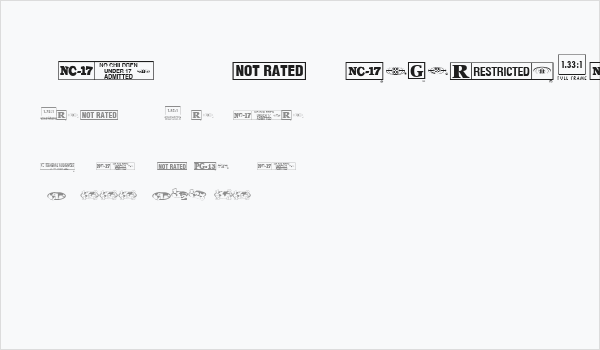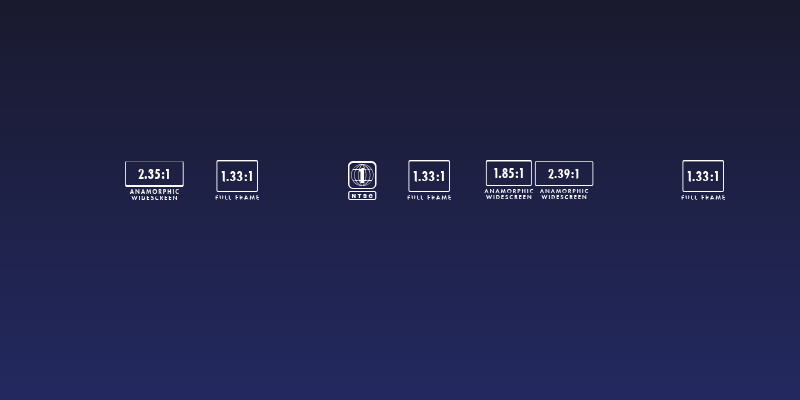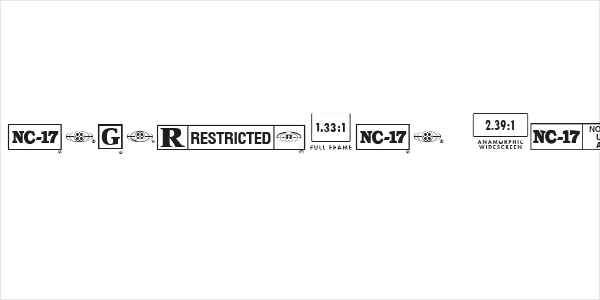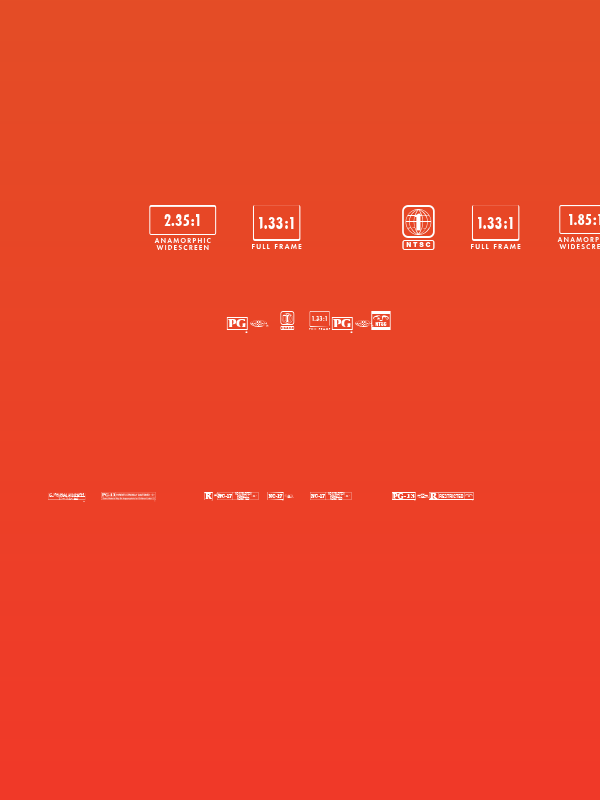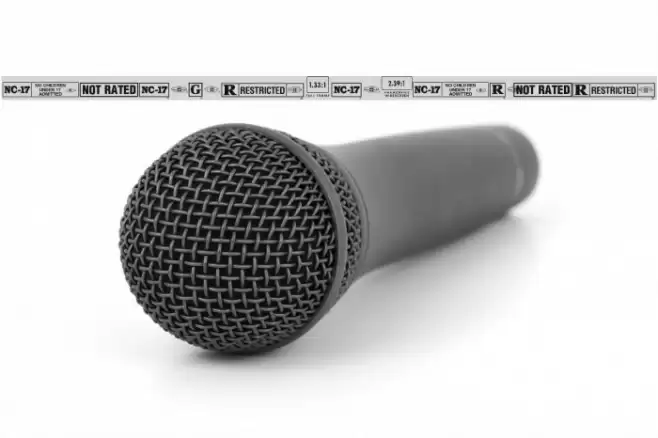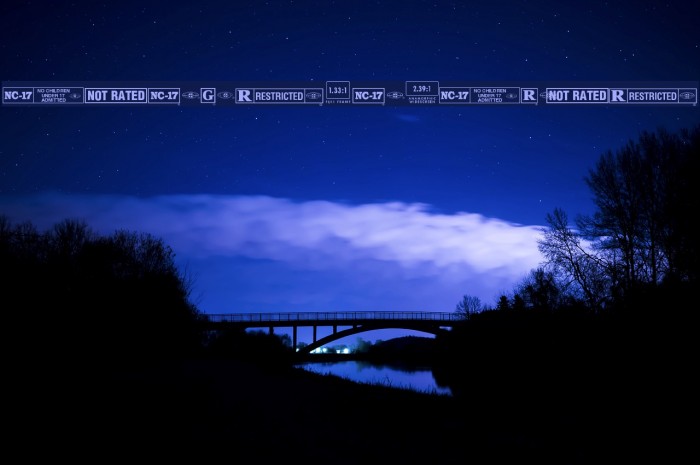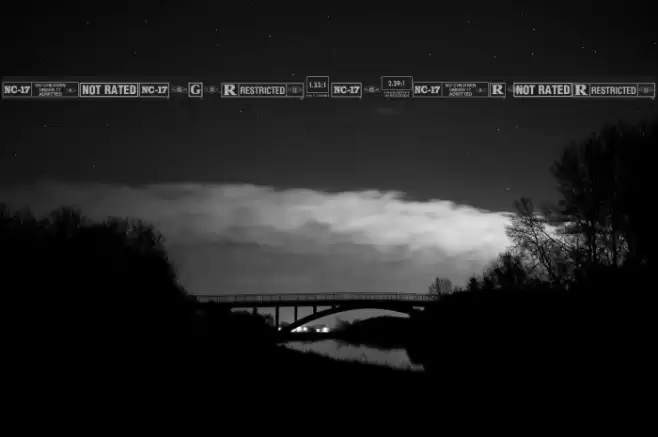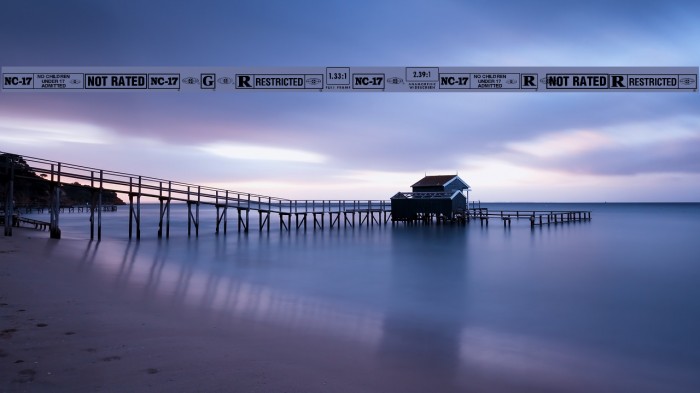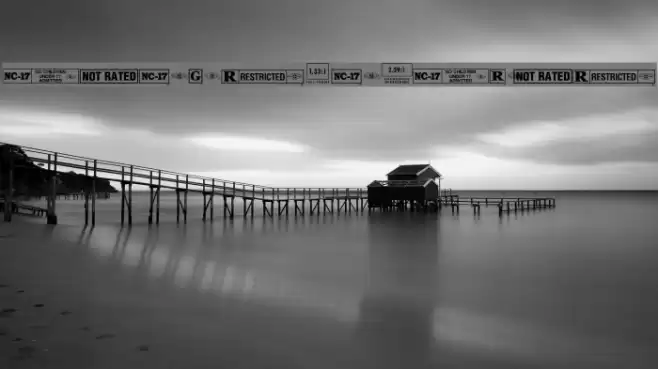
MovieRatingsAndFormats Font
| Style général | Utilitarian, Official, Modern |
| Cas d'utilisation | Labels, Ratings, Informational graphics, Packaging |
| Projets proposés | Movie rating labels, packaging, signage, instructional graphics, compliance documents. |